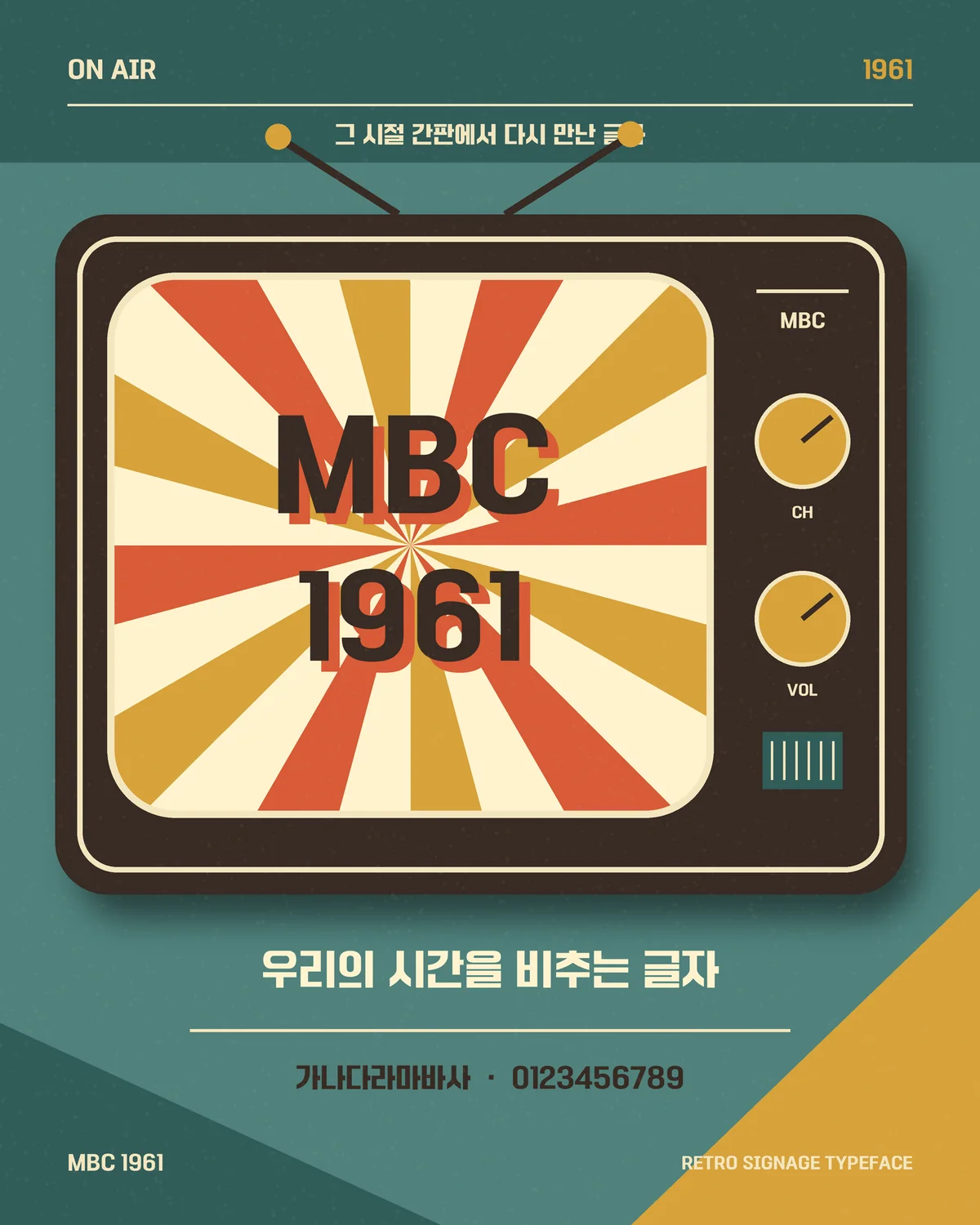
MBC1961 — (주)문화방송에서 배포하는 무료 폰트입니다. 1960년대 방송국 옛 간판의 형태를 현대적으로 재해석한 힘 있는 제목용 고딕체
문화방송이 창사 60주년을 맞아 2021년 첫날부터 무료로 푼 서체입니다. 이름의 1961은 개국 연도이고, 모티브는 1961년 MBC 인사동 사옥의 옛 간판입니다. 1960년대 모듈 형태의 간판 느낌을 현대적으로 재해석했다고 밝히고 있습니다.
같은 이름의 굴림체와 역할이 갈립니다. 제작사 설명에 따르면 굴림이 붙지 않은 이 서체가 신뢰받는 공영방송의 채널 정체성을 담았다면, 굴림 쪽은 국민에게 사랑받는 친근하고 레트로한 느낌을 맡습니다. 이쪽이 모듈형 간판의 각진 성질을 그대로 살린 제목용입니다.